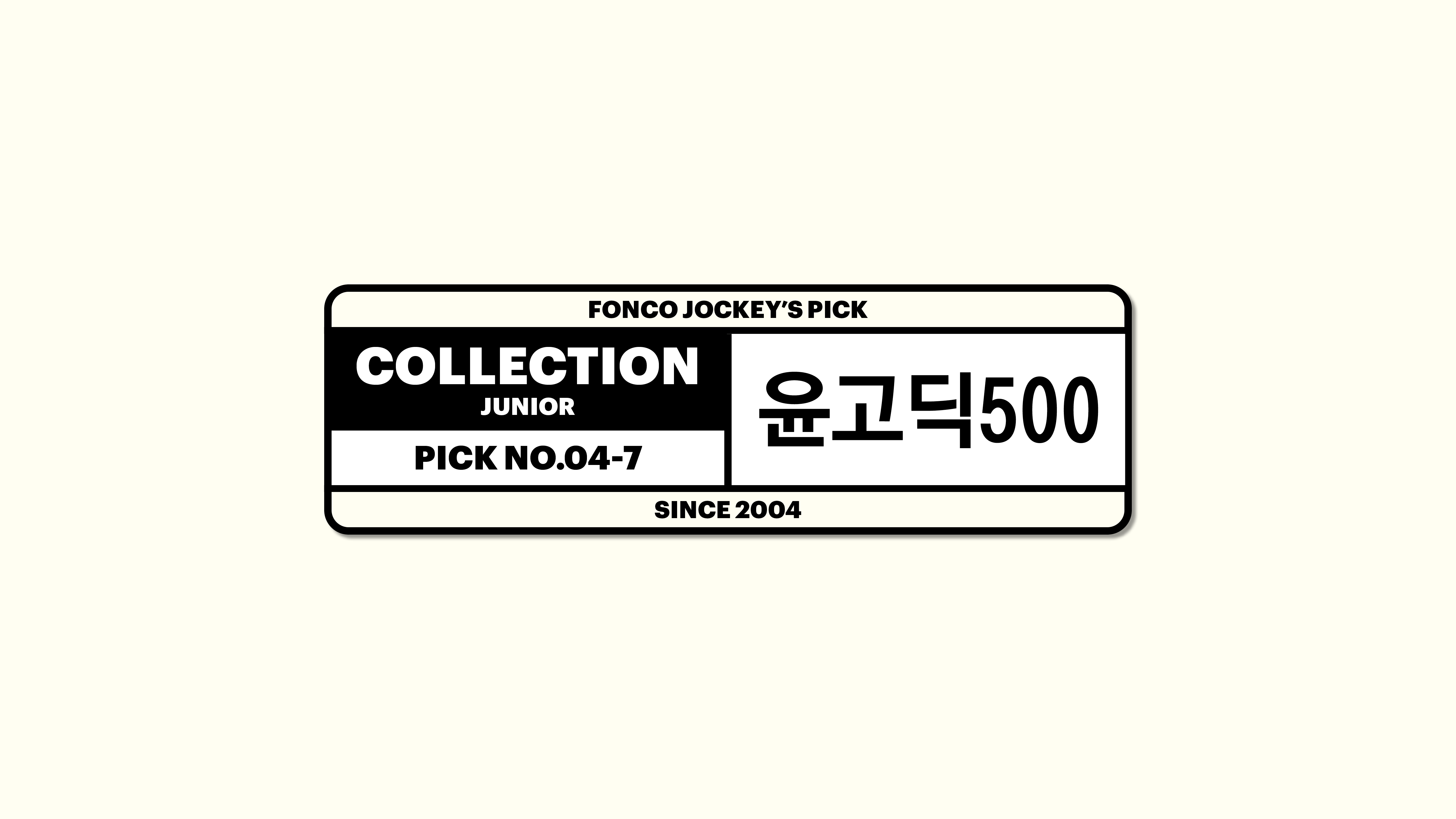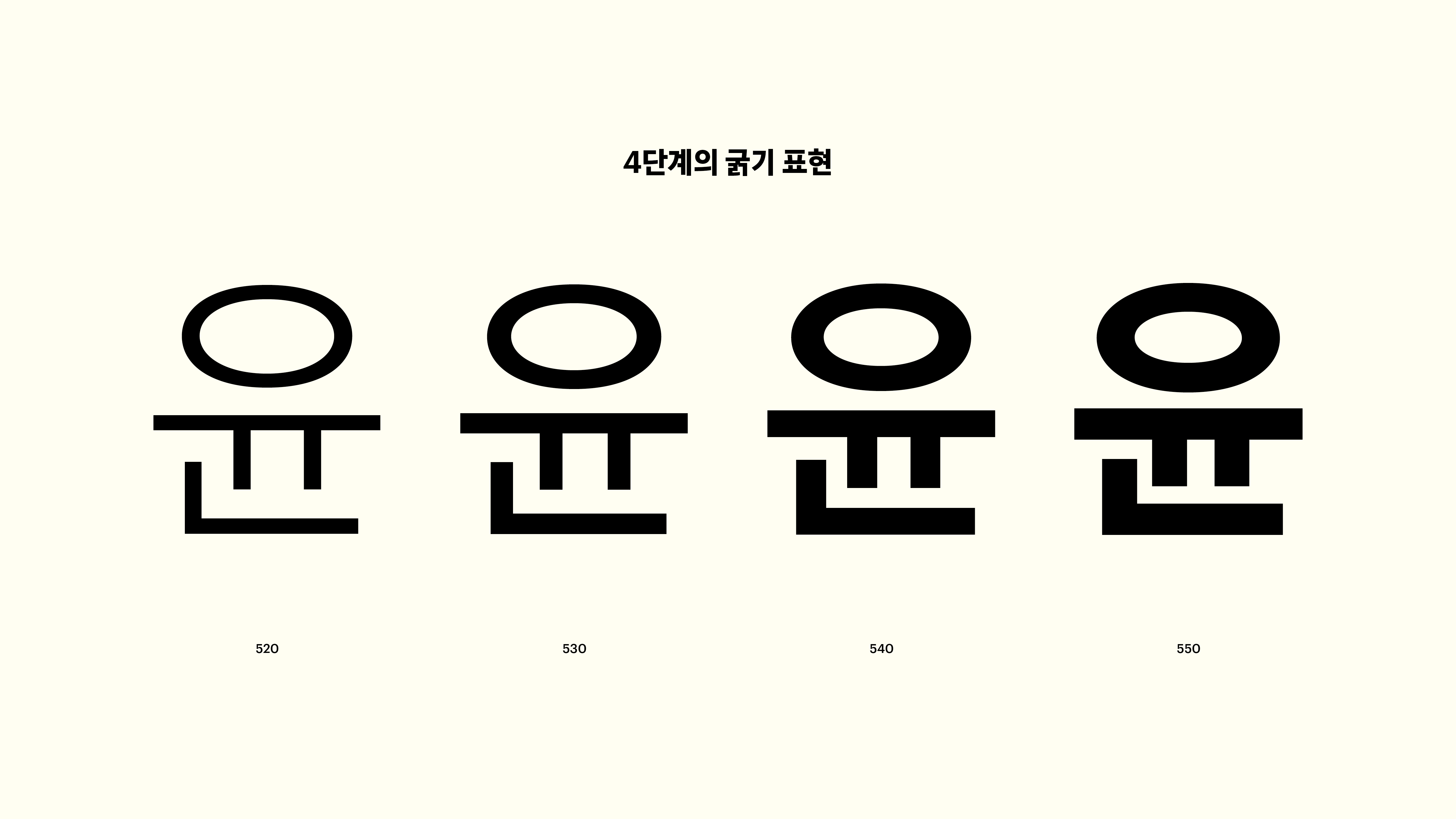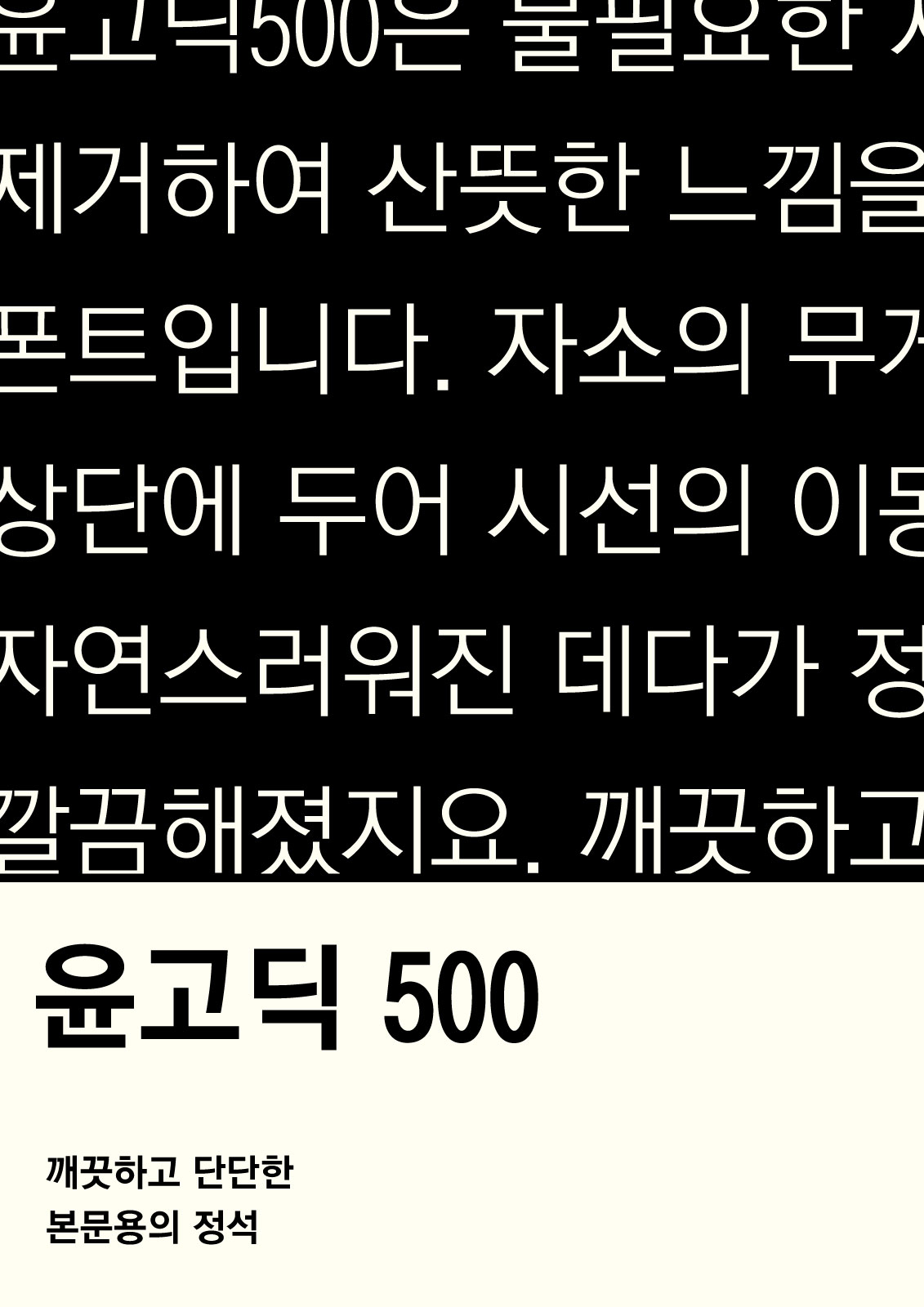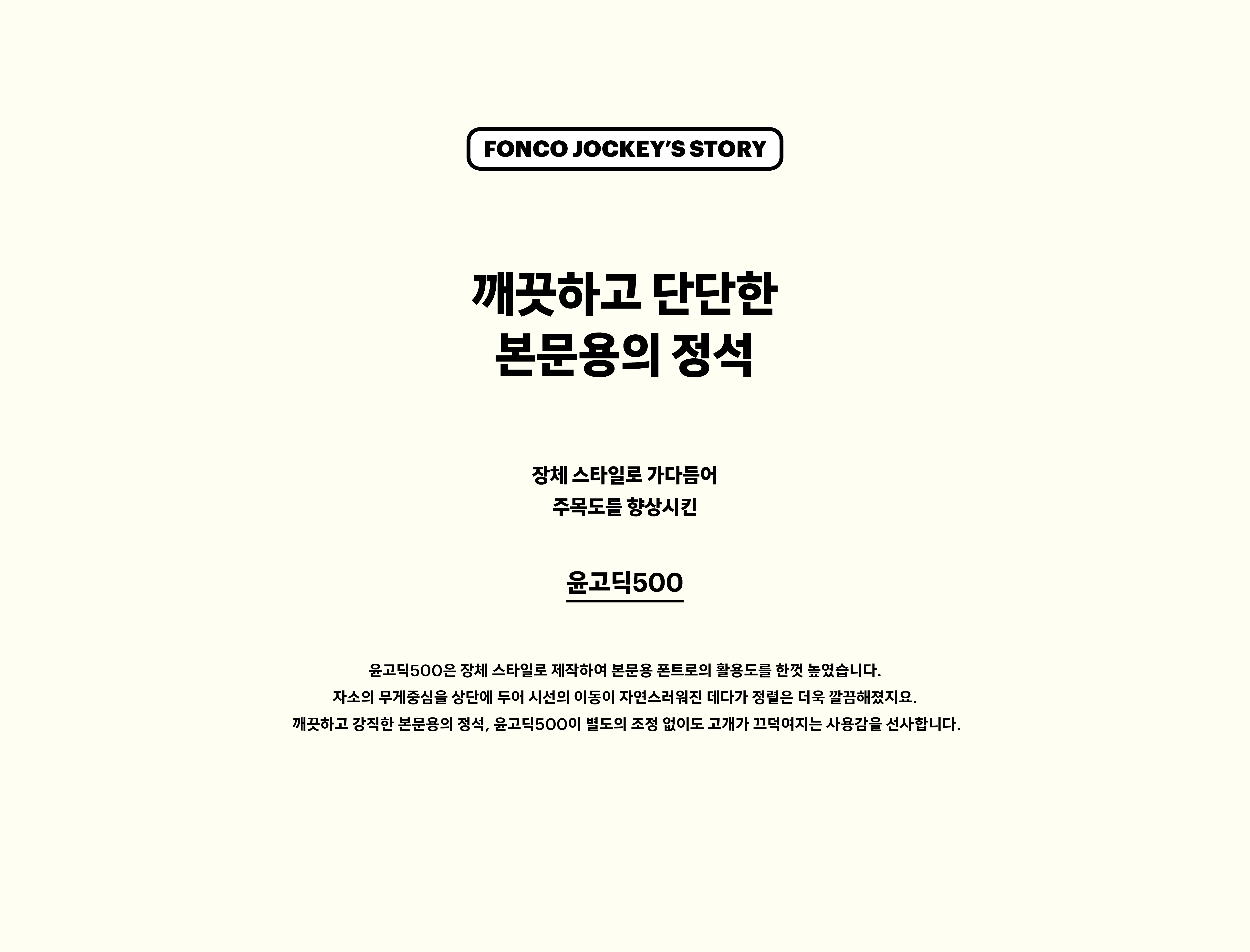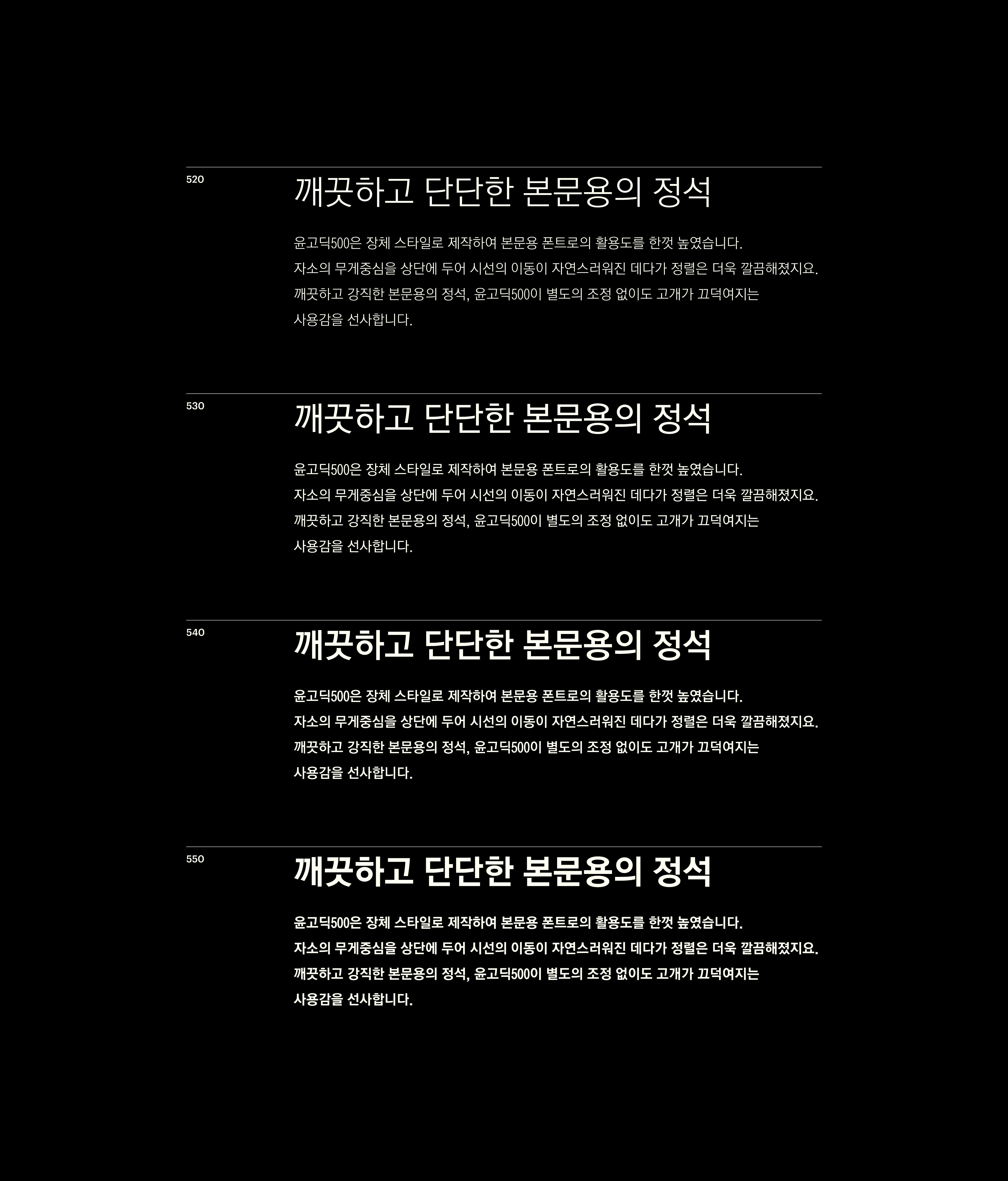
윤고딕 500
2000-2004
Yoon 윤고딕 500
윤고딕500은 불필요한 세리프를 제거하여 산뜻한 느낌을 한껏 살린 폰트입니다. 자소의 무게중심을 상단에 두어 시선의 이동이 자연스러워진 데다가 정렬은 더욱 깔끔해졌지요. 깨끗하고 강직한 고딕 중의 고딕. 언제, 어디서나 윤고딕500이 찰떡같은 사용감을 선사합니다.